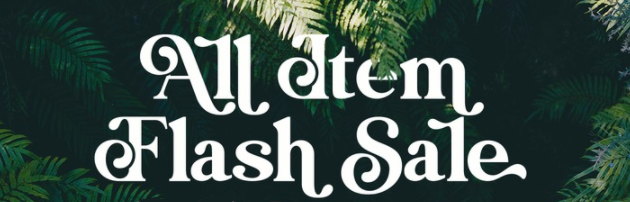
Представляем вам Rachel Brown!
Шикарный и современный шрифт с засечками.
Этот шрифт идеально подходит для брендинга, логотипов, социальных сетей, принтов, наклеек, футболок, svg-файлов и многого другого!
Rachel Brown уникален тем, что его можно использовать для различных стилей дизайна. Он прекрасно подходит для свободных, бохо дизайнов, а также для более стильных редакционных образов!
Есть много интересных стилистических альтернатив, которые можно использовать с этим шрифтом. Эти буквы встроены в файл шрифта и легко доступны в таких программах, как photoshop и illustrator.
Rachel Brown имеет широкий набор функций OpenType. При обычном использовании используйте стандартные лигатуры. Для нестандартных заголовков или логотипов используйте дискретные лигатуры, Swash, Stylistic или Titling Alternates.